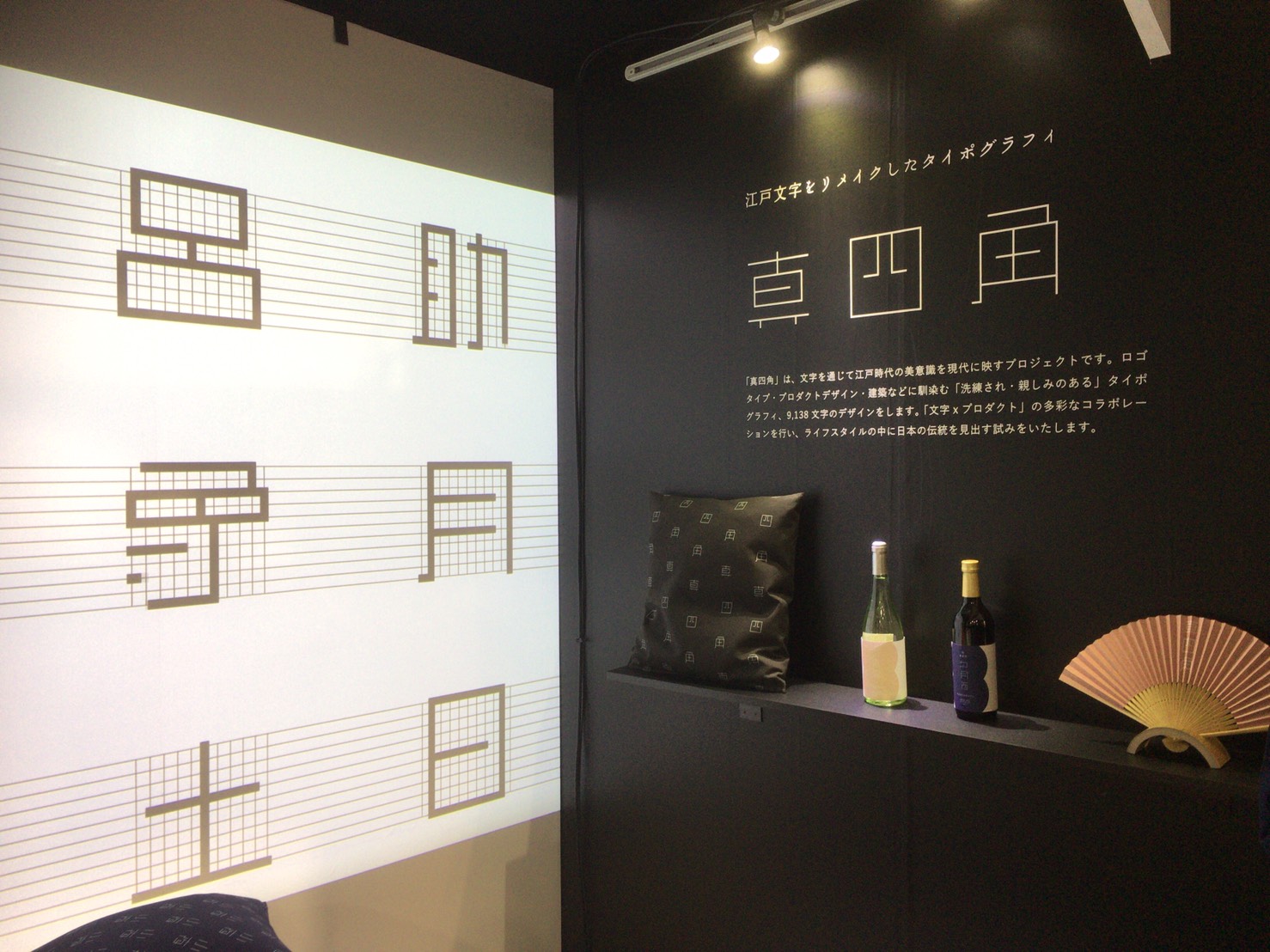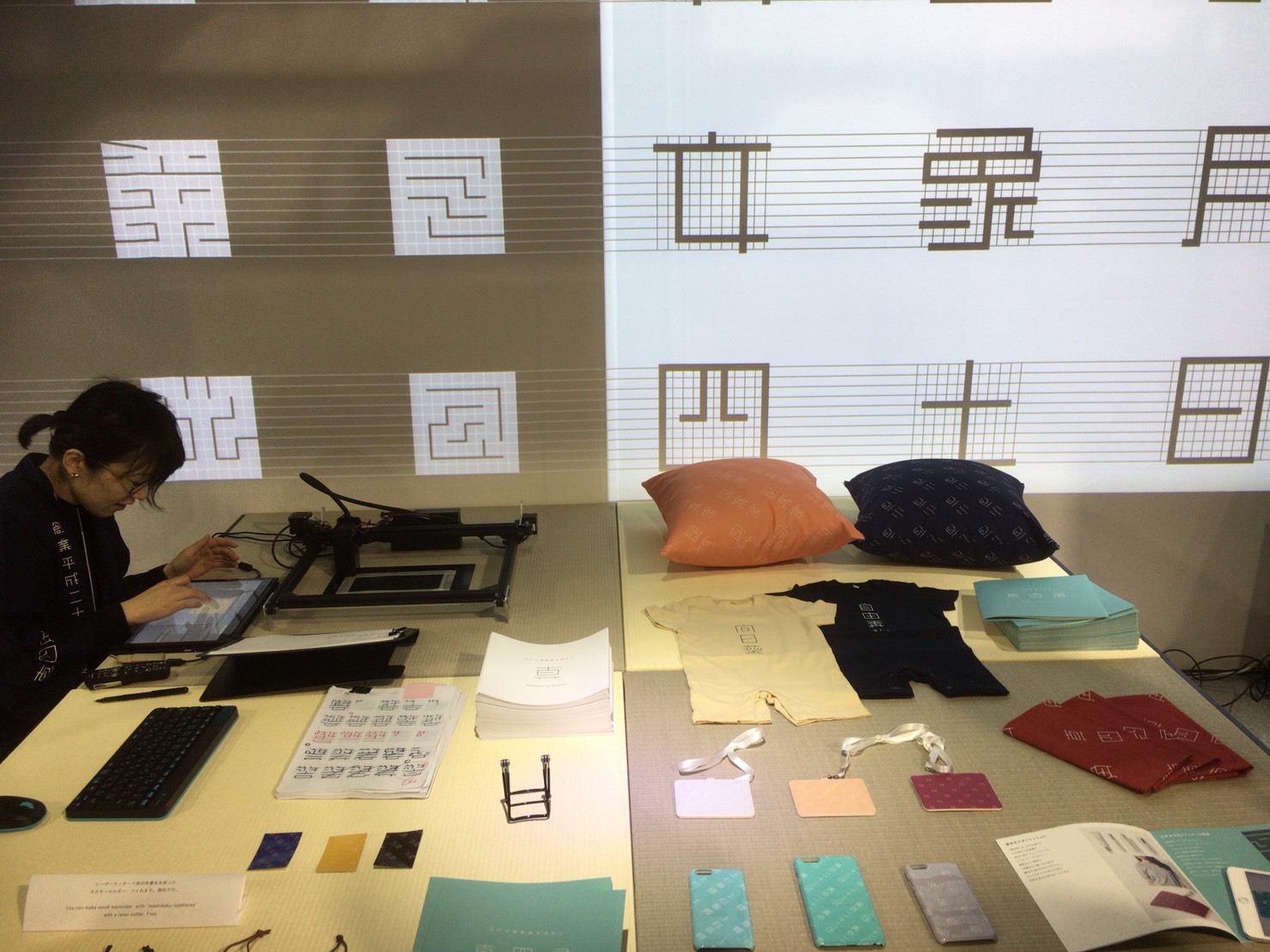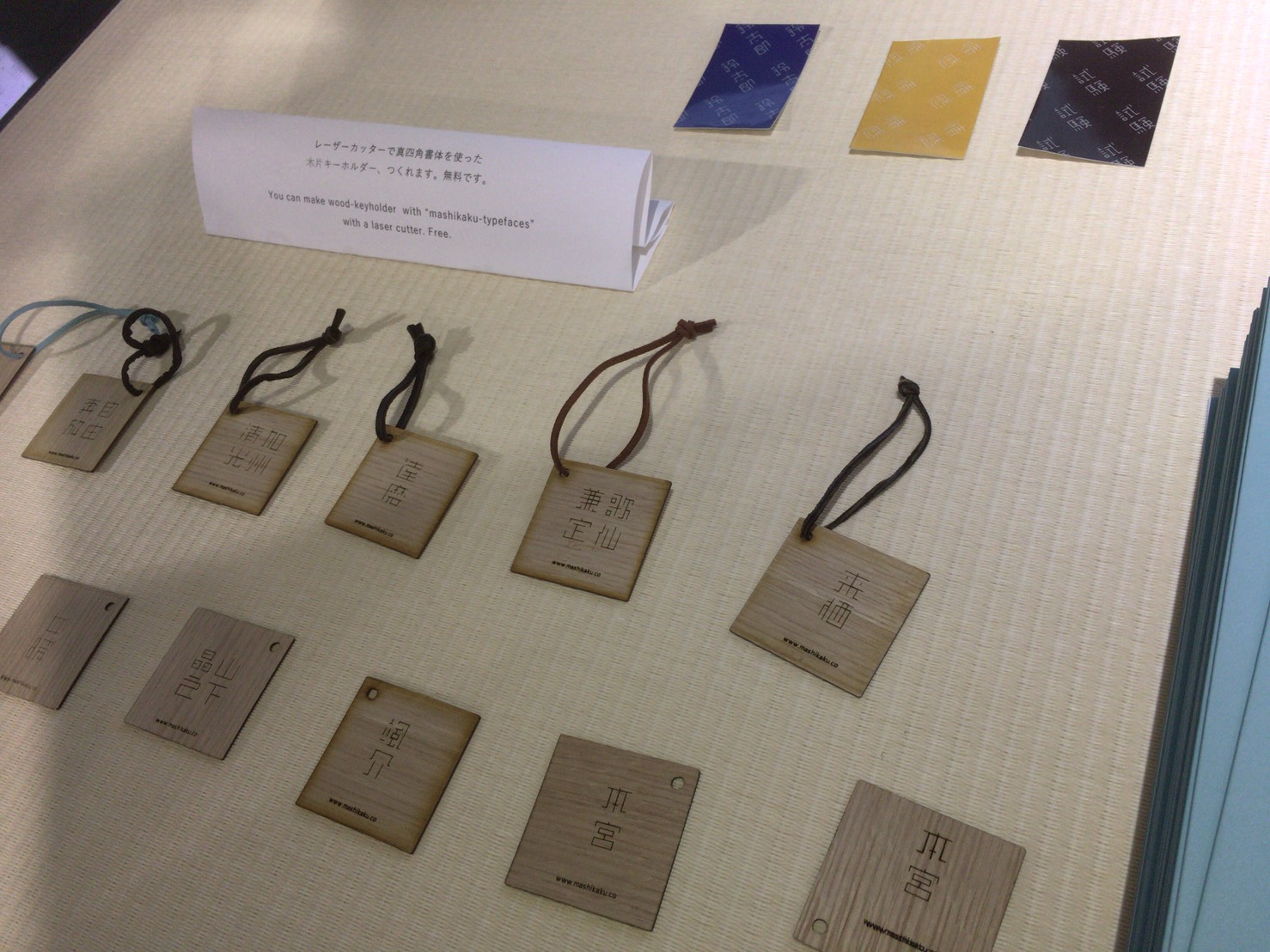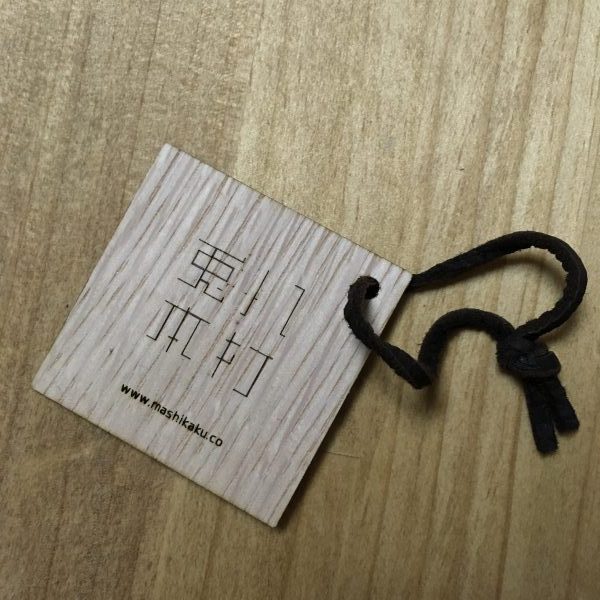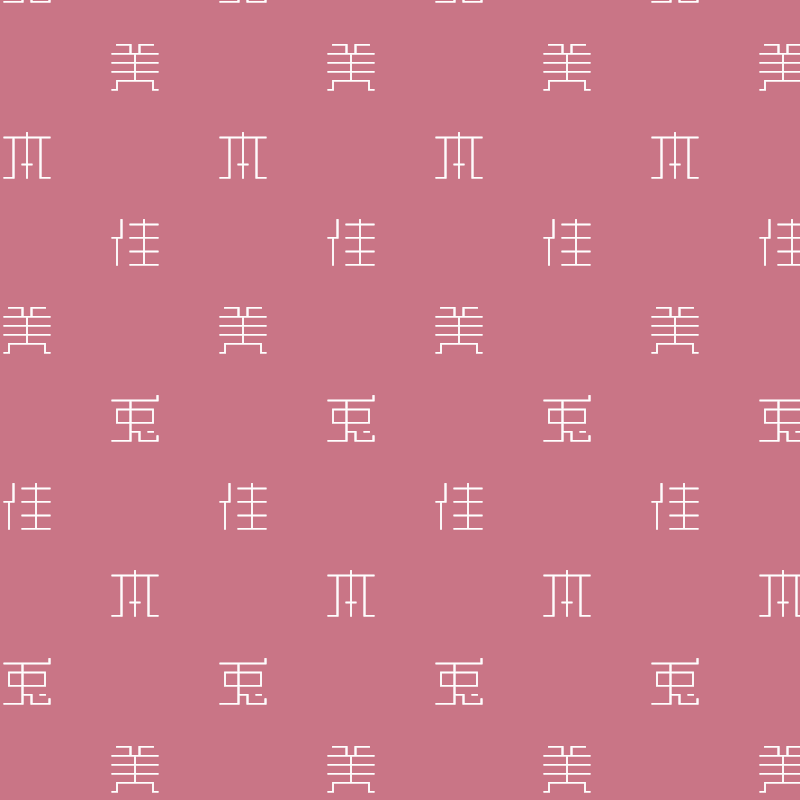
10月26日から始まった「東京デザインウィーク 前期」に行ってきました。初めて参加したのですが、実用的なデザインの数々に魅了されました(^^)/。その会場で「真四角フォント」というものをみつけました。このブログでも何度かフォントについて書いているように、かっこいい/かわいいフォントが大好きです。
フォントをレーザーカッターで焼き付けてくれたりして、おみやげもいただきました。実際にはWeb上から「真四角フォント」を使った商品を購入したり、ダウンロードすることもできるようなのでそれらについて書きます。
東京デザインウィーク で見つけた「真四角フォント」のブースでは、キーホルダーをもらいました!
絵画館前で行われている東京デザインウィークはこの写真で見ても分かるように、素敵なデザインがたくさん並んでいるたのしい展示会でした!
その中で見つけた「真四角フォント」のブースがこちらです。
この「真四角フォント」を見つけたとたんにその場にいた4人の人が一斉に駆け寄ったほど、印象的で素敵なフォントでした!
ブースでお話をしていたら
レーザーカッター を使って
キーホルダーを無料で作ってくださるということだったので、
作ってもらいました!八打兎本(8Beat兎本のつもり) って入れてもらいました。かっこいいです。
真四角フォントは
江戸文字の「角字」にインスパイアされて作成されたフォントということです。
すると、赤ちゃんのロンパースからスマホケースなど、商品がどんなイメージになるかもその場で確認できます。
このように複数のレイアウトから選ぶことができて、さらに
さっそく先ほどのように色を変えて作ってみました!
さっきは気づいていなかったのですが、ここから文字の大きさを変えることができるみたいです